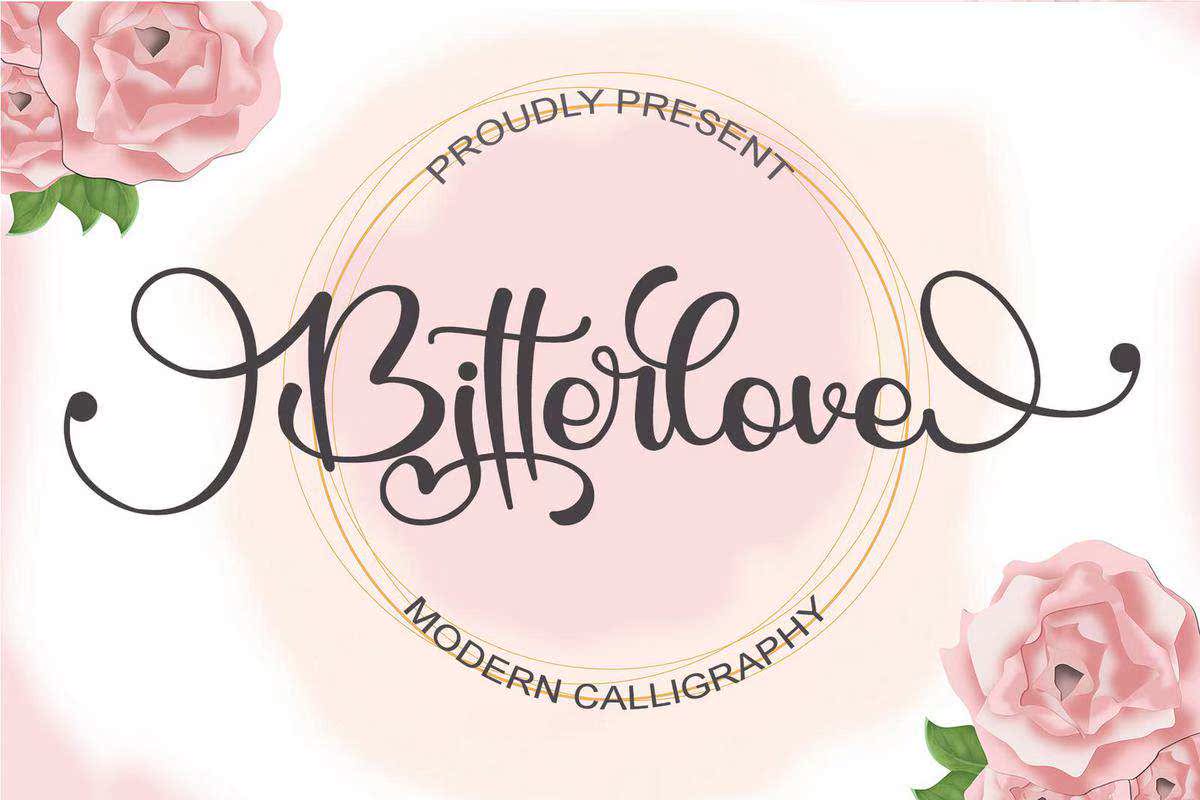
Lovelyspring Bundle是一个字体集合。21种字体,1个包装,其中包含现代字体/脚本字体和手写字体。iSettleSpecialPrices从总计210美元到7美元。这只适合你。Lovelyspring Bundle是一个字体集合。21种字体,1个包装,其中包含现代字体/脚本字体和手写字体。iSettleSpecialPrices从总计210美元到7美元大约210到7美元,都是给你的。